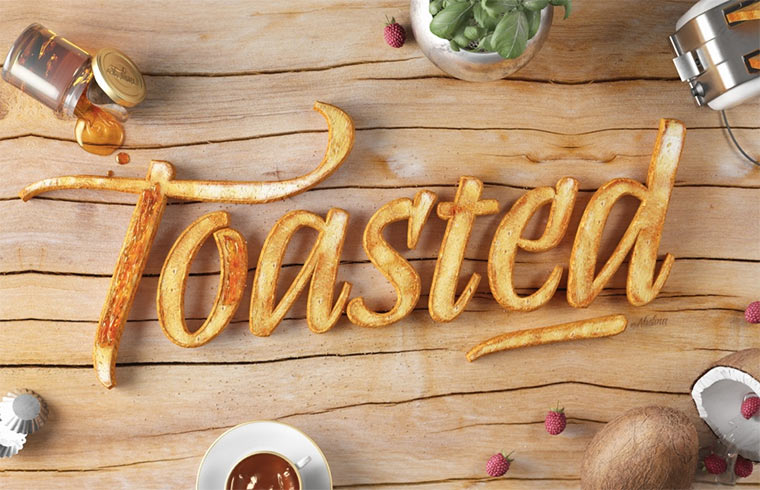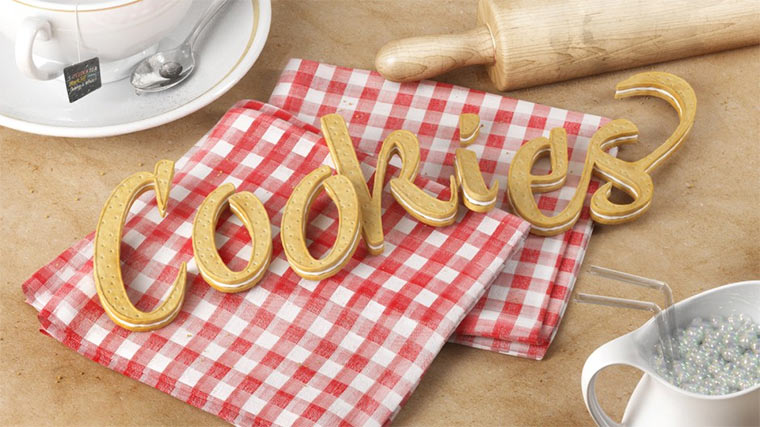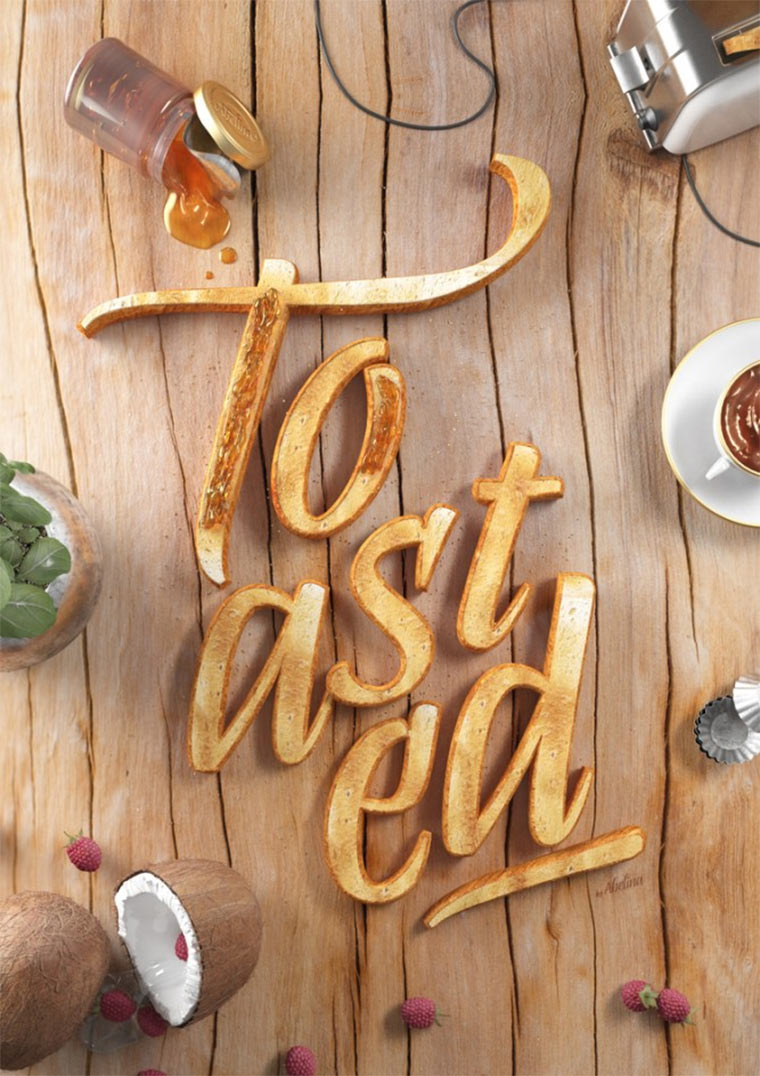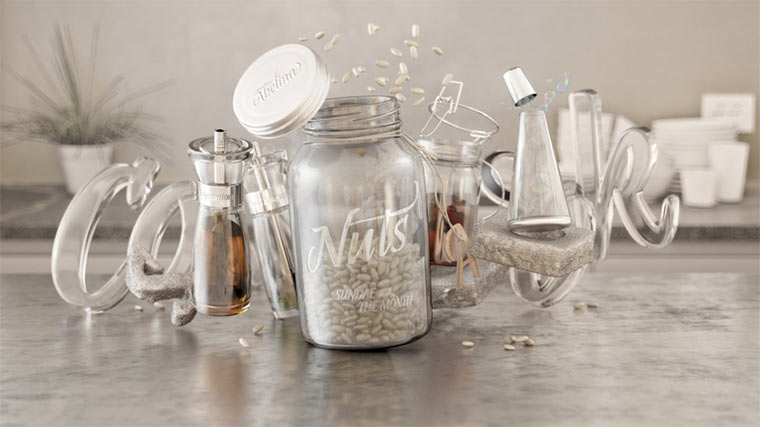
Schmackhafte Kreationen
Typografie: Six & Five
Das Design Studio Six & Five ist spezialisiert auf 3D-Arbeiten. Zur Bewerbung der neuen Schriftart Eblina von der Grafik-Designerin Yanina Arabena haben sie sich einige sehr kreative Typografie-Motive ausgesucht. Dieses Toasted-Design ist dabei mein absoluter Favorit.